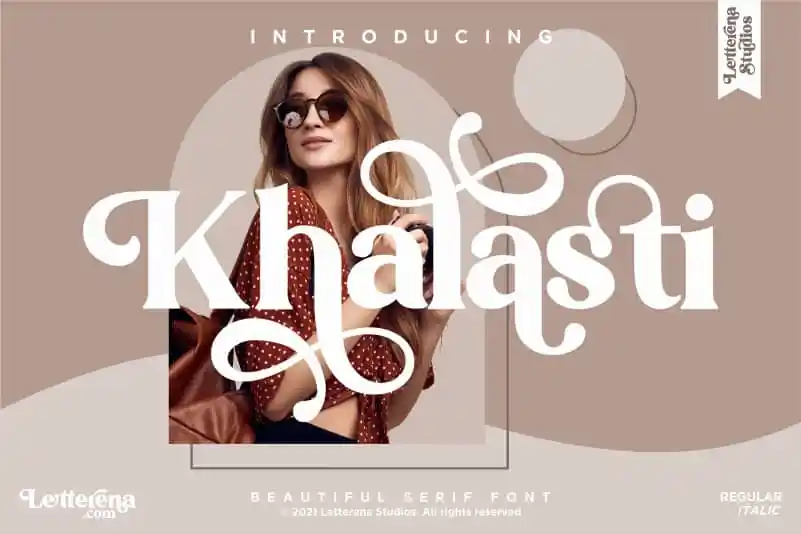
Khalasti Font – Download Grátis
A Khalasti Serif é uma fonte serif que traz elegância para qualquer projeto. Desenvolvida por Letterenastudios, ela se destaca como uma opção perfeita para trabalhos de alto padrão. Seja você um designer de logotipos ou criações em homenagem à casa, criando pacotes de produtos, estampando café, desenvolvendo cartazes, projetando sacolas de compras e camisetas, a Khalasti é sua fonte perfeita. Através da Khalasti você pode criar cartões de nome, convites, cartas de cumprimentos, etiquetas, fotos ou até mesmo para eventos especiais que exigem uma pitada sofisticada e elegante do mundo serif. Este é o ideal para projetos caprichados e belos que precisam ganhar um toque de luxo. Seja qual seja seu projeto, a Khalasti estará à sua disposição para ajudar a dar vida ao design mais sofisticado.